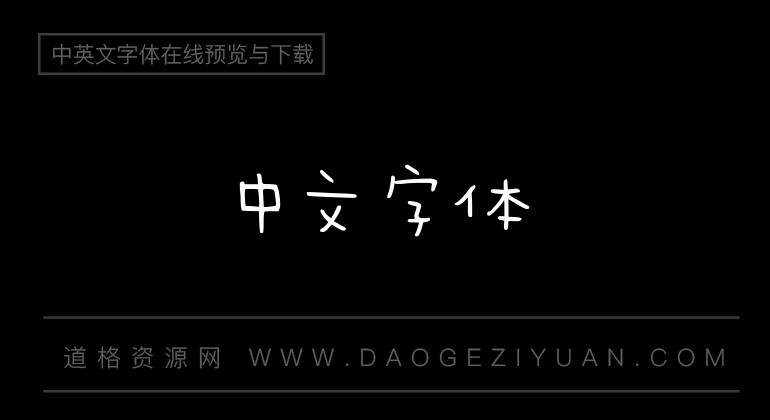
手帐体是一种草书字体,最初由中国画家顾恺之于19世纪初期创作,以其简洁大方的笔画、细腻的曲线及完美的结构而著称。手帐体是一种自由、活泼、明快的字体,有着流畅的笔画,让字体看起来更加活泼。此外,它还具有独特的结构,可以更好地展示文字的美感。它的曲线流畅、结构严谨,可以更好地表达文字的精神内涵。文件名:ShouZhangTi-2.ttf
手帐体是一款非常不错的手写艺术字体,具有很好的视觉感,适合于文化类的宣传设计、商业类品牌的广告和产品包装设计以及个性化文字排版等较多场景。